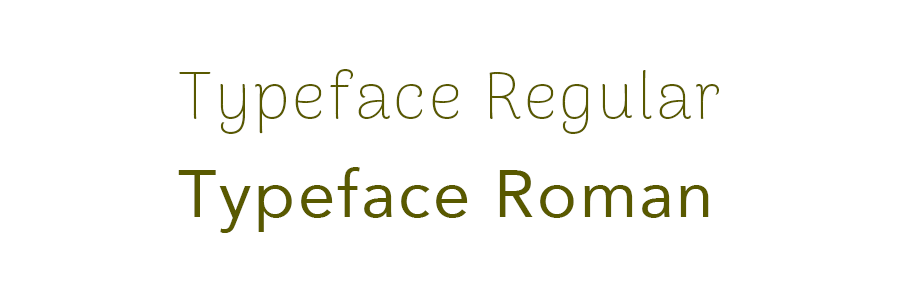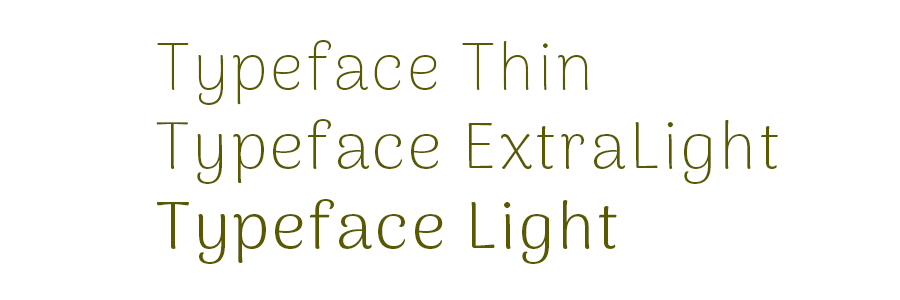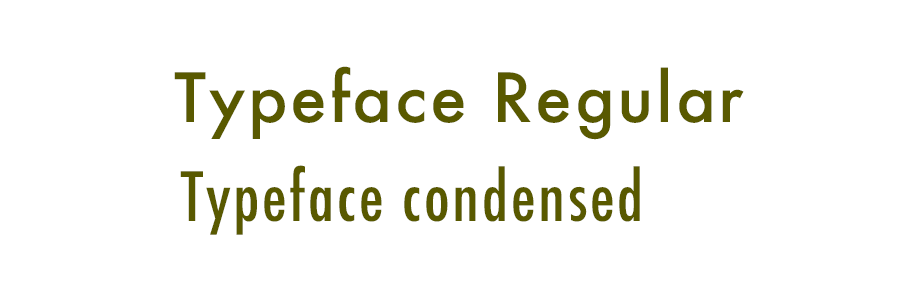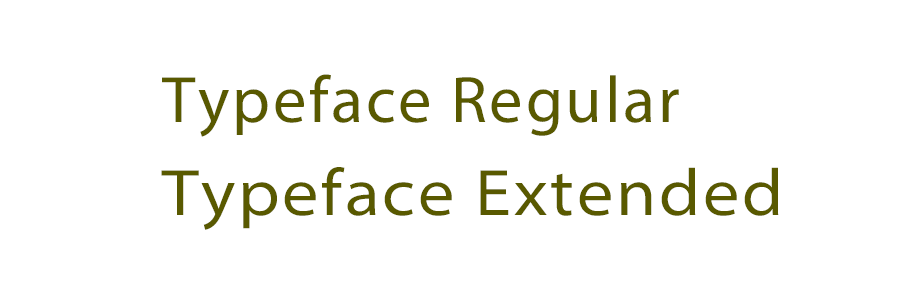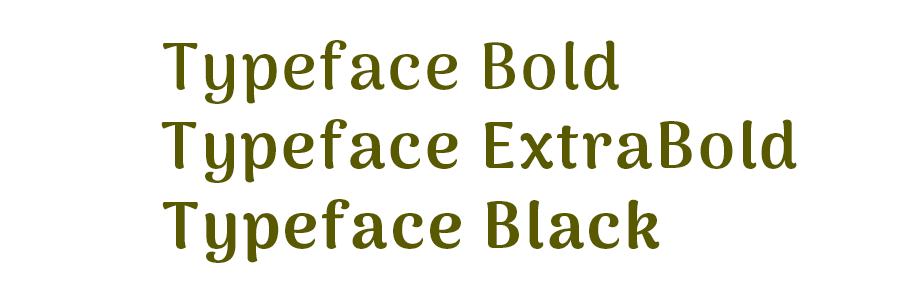
在西方字体家族中,会根据笔画的粗细差异,在名称后附加相应的字重标识。以下是一些标准且常见的字重名称:
Light:专为标题设计的细体字重,在无衬线字体家族中尤为常见,尽管某些罗马体也具备此字重。比Light更细的字体还有Thin或Extra Light等。
Regular/Normal/Roman:被定义为“标准”的字重,其粗细适中,非常适合日常阅读与排版。许多无衬线字体将这一字重称为“Roman”,其含义与Regular相同。
Medium:位于Regular与Bold之间的字重,部分字体家族在Medium与Bold之间还提供了Demi或Semi等中间字重版本。
Bold:指线条较粗的字重。当Regular用于正文排版时,与之搭配的标题往往采用Bold字重以增强视觉冲击力。比Bold更粗的字体还有Extra Bold、Heavy、Black等。
关于字宽的变化:
Condensed:常见于无衬线字体,Condensed字体常用于大标题,且通常不会与标准字宽的字体在同一行中混用。
Extended/Expanded:专为标题设计,具有更宽的字体宽度,以展现独特的视觉效果。